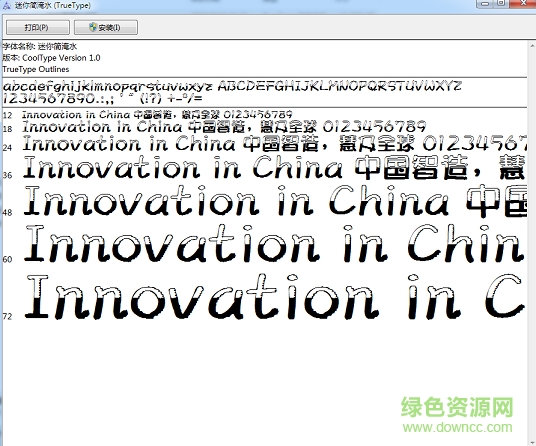
迷你簡(jiǎn)淹水是一款看上去非常特別的字體,該字體端莊雄秀、神韻超逸、圓融蒼潤(rùn),看上去十分美觀,整體效果非常統(tǒng)一,且字庫(kù)完整,喜歡的朋友歡迎來(lái)綠色資源網(wǎng)下載!
迷你簡(jiǎn)淹水是一款可以廣泛應(yīng)用于美術(shù)設(shè)計(jì)、新聞媒體、宣傳海報(bào)、ppt、影視制作以及內(nèi)容用字等領(lǐng)域的字體!